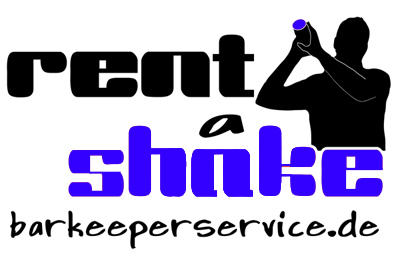
Welche Schriftarten sind das
wir haben folgendes Problem. Unser logo muß quasi druckfertig gemacht werden.
leider habe ich das logo nur als jpg vorliegen und will es nun, um eine vektorgrafik daraus machen zu können neu aufsetzen. leider wissen wir partout nicht mehr welche schrift wir benutzt haben. alle auf dem rechner ausprobierten passen nicht überein. allerdings haben wir diesen auch neu aufgesetzt, wahrscheinlich sind dabei alle installierten schriftarten verloren gegangen...
wir haben schon rausgefunden, dass das a ledilgich eine verzerrte variante der untersten schrift ist. doch was ist mit dem rest....
vielleicht kann uns ja jemand helfen und die vorhandenen schriftarten identifizieren...
Habt Ihr schon einmal daran gedacht, statt Energie aufzuwenden, um das bestehende Logo druckfertig zu machen, lieber die Schrift des Logos auszutauschen und somit das Logo neu aufzubauen?
Das wäre sicher weniger Arbeit und würde vielleicht besser aussehen.
sicher, in diesem fall schon.
nur doof wenn bereits die visitenkarten,
t-shirts und die autobeschriftung genau diese schrift hat,
die briefbogen dann jedoch anders aussehen.
habe gesucht aber nichts gefunden.
daran haben wir auch schon gedacht. Nur haben wir damals schon Geld für das logo bezahlt (leider Vorkasse) und nie die vektordaten erhalten. haben es mittlerweile aufgegeben und versuchen unser Prob nun so zu lösen.
andere schriften wären natürlich auch eine alternative, jedoch haben wir eben dieses logo schon "verteilt", also aufkleber, visitenkarten etc... dazu langte ja die jpg-qualität...
aber die schrift kann doch nicht so außergewöhnlich sein...
habe schon bei "whatthefont" geschaut, jedoch nix...
Das habt ihr so gedruckt?
Das ist doch ein RGB-Blau – eigentlich recht unbrauchbar für den Printeinsatz.
Zum Thema. Es dürfte doch kein Problem sein die Schrift unten peu a peu durch eine ähnliche zu ersetzen, von denen es sicherlich zuhauf als Freeware gibt.
yo, haben wir dann auch bemerkt... lief eher ins lila, als ins blau...
also dafont und t26 bin ich durch - nix.
massig ähnliche, aber nicht dieser,
dass 'a' von shake sieht komisch aus,
vielleicht wurde da was abgeschnitten ...
Genau.. oder 'ne blöde Schriftensammlung. Ahm. Ja.
Und dann wird der Auftrag noch nach und nach aufgebohrt. Erst wollen sie
"nur mal eben" ein Schild oder ein Logo. Dann sollen's auf einmal auch noch Visitenkarten sein oder so was.. kennt man ja. *hüstel*
eigentlich wollte ich lediglich wissen um welche schriftart es sich hier handelt... und keine sinnlose diskussion über preise herbeiführen...
Logo wurde ordnungsgenäß bezahlt, allerdings kam dann außer ein paar Vorschlägen in JPG Qualität leider nicht viel...
zum thema design
also uns gefällt das logo eigentlich ganz gut. das motiv mit dem barkeeper stammt von einem foto von uns.
wenn jemadn bessere logo-vorschläge hat, kann er sie gerne zusenden. sollte was pasendes dabei sein, sind wir gerne bereit dafür zu zahlen.
leider kommt auf die weise selten was vernünftiges rum.
es geht darum, dass das logo technisch nicht gut funktioniert, die farbe, die details ... es hat jemand ohne druckerfahrung gemacht, das ist halt schade und ihr habt jetzt den ärger.
wir helfen hier alle gerne aber bei solchen freefonts hat kaum jemand erfahrung um es zu sagen was es ist, auch wen manche den ehrgeiz haben es rauszubekommen.
du nimmst für deine mixgetränke auch nur hochwertige zutaten, oder?
hi, das ist wahrscheinlich wie überall - es richtet sich immer nach dem preis.
leider bin ich im bezug auf layout auch nur alie, so dass ich das schlecht beurteilen kann. es ist eben nur, dass uns das logo gefällt und wir es gerne weiterverwenden würden...
wir dachten eben eigentlich, dass dieser jemand über die nötige erfahrung verfügt...
und wir haben oft solche kunden die erst nach ne weile oder bis die ersten probleme auftachen merken, dass sie jemand schlecht bedient hat.
das logo an sich sollte sehr einfach gehalten werden, da wir dieses auch z.b. sticken lassen wollen. daher wenn möglich immer das gleiche...
jetzt hat sich ein designer bei uns über das forum gemeldet, der uns eine neu schruft schonmal einbauen will und das ganze vektorisiert. erste vorschläge sehen auch schon brauchbar aus.